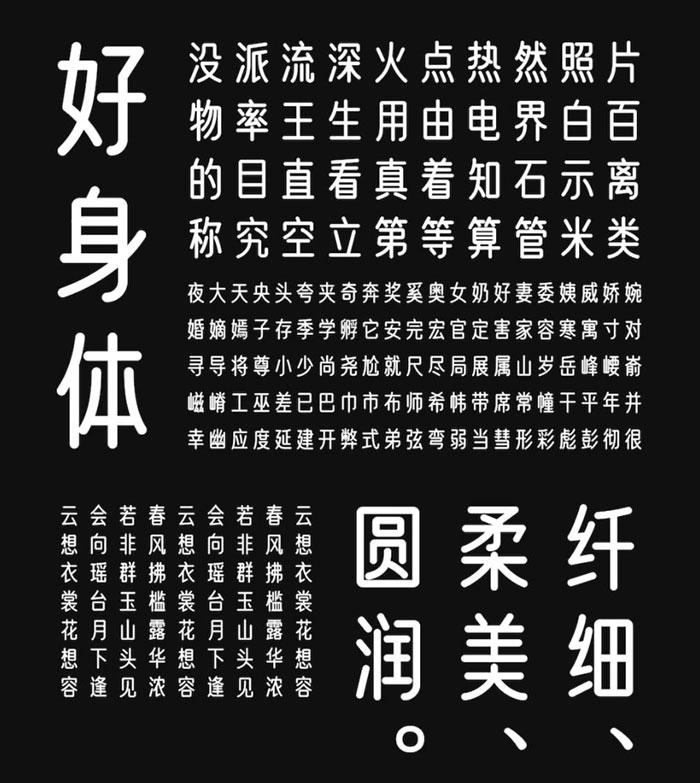
與「優設標題黑」沉穩有力兼具速度感的思路不同,「優設好身體」的整體氣質偏向圓柔纖細,設計上更加富有親和力和現代感,2套字體互為補充,可以覆蓋絕大多數的設計場景。
優設好身體是一款親和力、現代感極強的專業美術標題字體。它以圓體字型為基礎,通過瘦高的字面、偏向幾何的曲線,讓整寬字體富有親和力和時尚感。在同樣的面積裡,更窄的字面就意味著能容納更多的信息,所以這款字體非常適用在需要體現親和力與時尚感的各類品牌宣傳廣告和產品包裝設計的標題上。